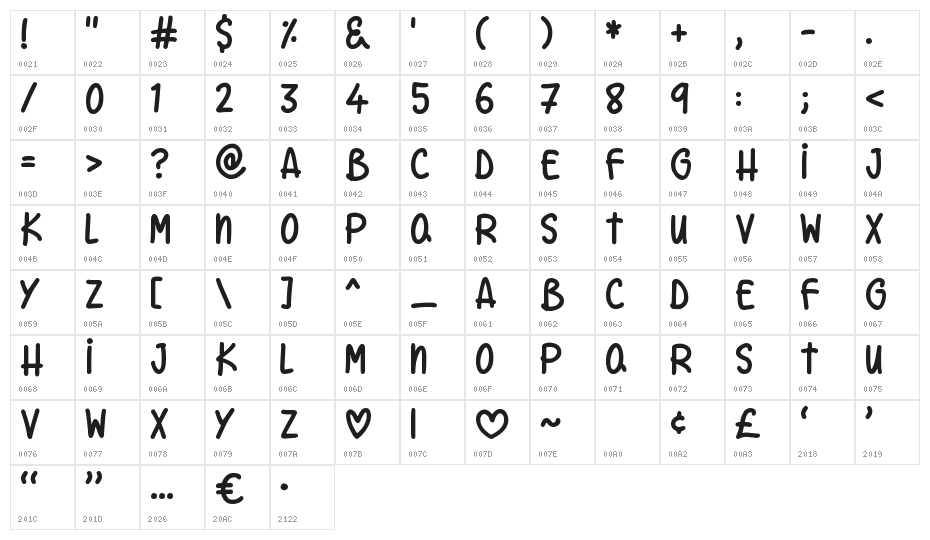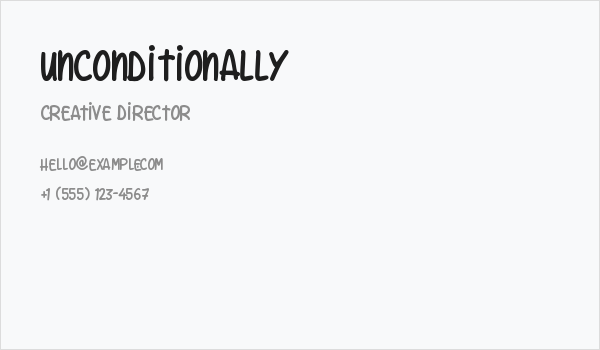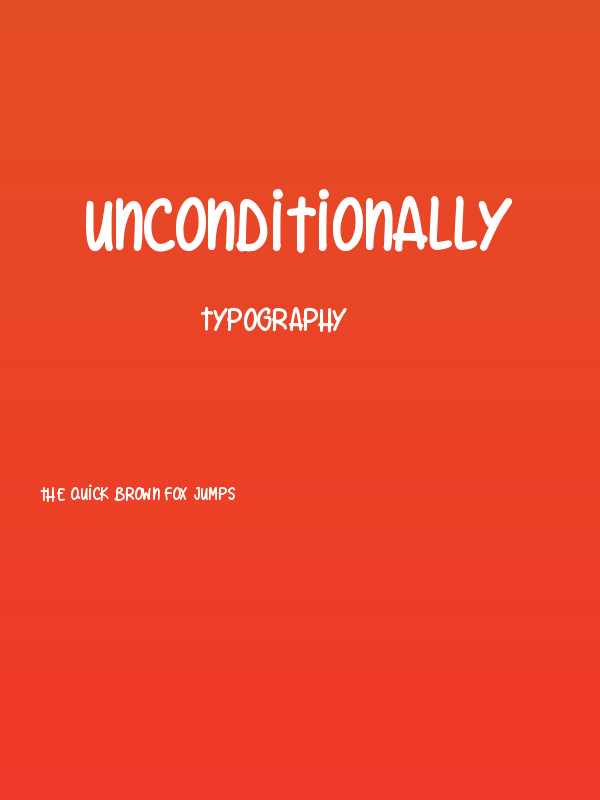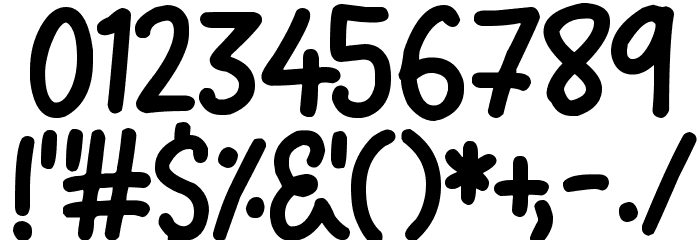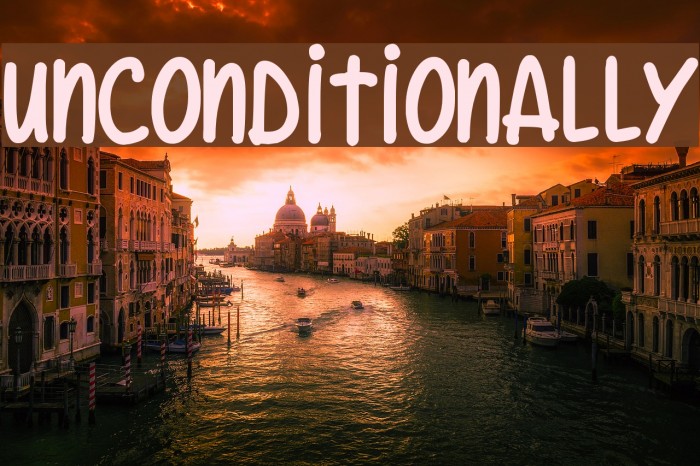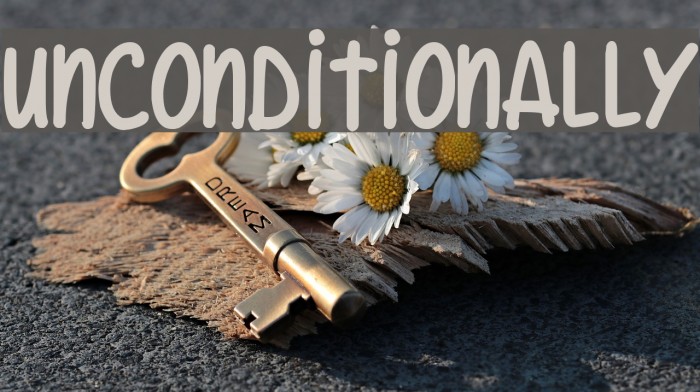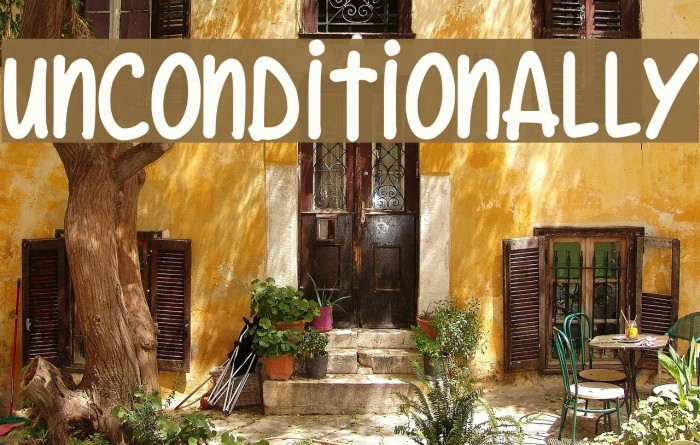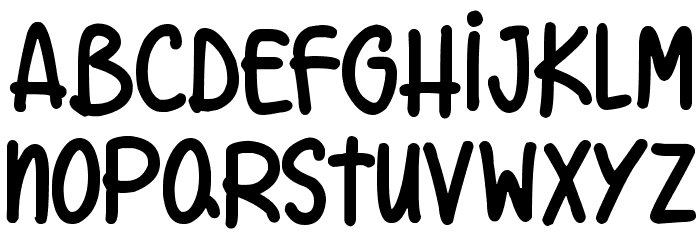
Unconditionally Font
Darrell Flood
| Estilo general | Playful |
| Caso de uso | Logos, Headlines, Invitations |
| Proyectos propuestos | Ideal for greeting cards, children's books, playful branding, and casual invitations. |